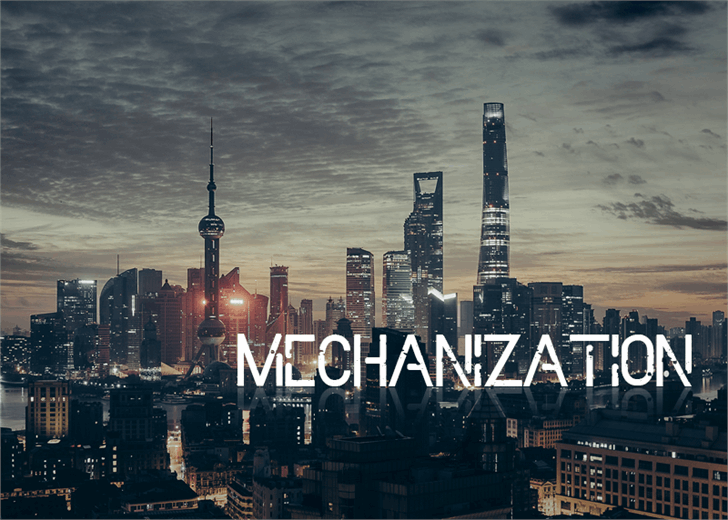
Mechanization Font – Download Grátis
Através do designer Hamilton, a font Mechanization é uma escolha ideal para aqueles buscando adicionar um toque nostálgico e único às suas criações digitais. Inspirada nas imagens pixeladas dos anos 80 e 90, esta font pixelizada oferece um estilo vibrante e minimalista que combina perfeitamente em designs modernos ou projetos vintage. Com uma disposição clara e tipografia de alta resolução, a Mechanization se destaca por seu design cuidadoso onde cada caractere é detalhadamente projetado para garantir uma legibilidade incrível. Ideal tanto para o uso em letras grandes em websites quanto para elementos gráficos interativos em aplicativos, esta font pixelada oferece um encaixe perfeito sem comprometer a qualidade. Seja você criando uma interface de usuário moderna ou produzindo artigos vintage com estilo, a Mechanization é uma escolha sólida que certamente valorizará o seu trabalho. Se procura uma fonte que combine elegância clássica com um toque moderno e único, então esta font pixelizada pode ser o elemento perfeito para seus projetos.